在中国的商业设计里面是离不开汉字的,可是很多设计师在做所谓的私人创作时往往就回避汉字,全是清一色的英文字母。汉字的编排其实很能见一个设计师的功力,大一点说作品里面文字的编排与设计就能看出这个设计师够不够老到。我很喜欢日本的设计,很大一部分原因就是他们的汉字编排。看一看怎么说汉字的编排吧,如果你是一个认真的设计师,相信耐心看完肯定大有收获的。
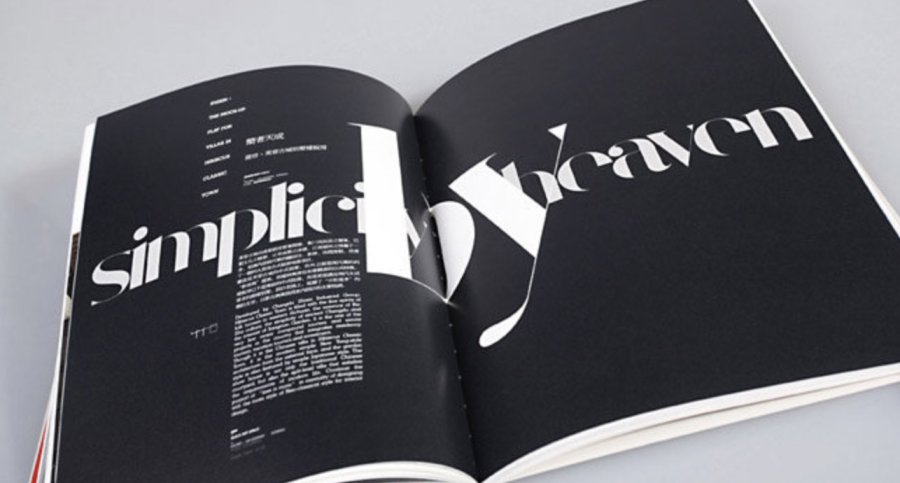
先要说一说汉字与拉丁字母的区别:字母是一种纯粹发音符号,每个字母本身并没有意义,单词的意义来自于这些字母之间的横向串式组合,而汉字的组字方式是以象形为原始基础,也就是每个字都具有特别的意义,一个简单的字可能在远古时代就代表了一个复杂的生活场景,因而它也是世界上最形象的文字。两者之间的阅读方式和解读方式都有本质的不同,因此,汉字的编排不能照搬英文的编排方式,它们两者之间在编排上有一些客观的区别。
首先,就是同样字号的实际大小不同,英文因为都是字母,字母的构成结构非常简单,一般在印刷上3号大小的英文都能清晰可辨,而汉字因为结构的复杂,在印刷上5号字已经接近辨认极限了,因而在设计时汉字因为要考虑可阅读性,在设计中就不如英文的字号大小灵活多变。还有英文字母线条比较流畅,因为弧线多,所以画面容易产生动感,这一点上比汉字生动多变。
第二,就是英文编排容易成"段",因为英文每个单词都有相当的横向长度,有时一个单词就相当于中文一句话的长度,单词之间是以空格做为区分,所以英文在排版时,哪怕是一句话,也大多做为"段"来考虑编排;而这点中文就完全不同,中文的每个字占的字符空间一样,非常规整,一句话的长度在一般情况下是不能拆成"段"来处理,所以中文在排版的自由性和灵活性上比不上英文,各种限制严格得多。虽然现代设计中有大量的对汉字进行解构的实验作品和商业作品,但总体来说,还是不能大量推广,毕竟,这种实验牺牲的就是人们习惯的汉字阅读的方便性。汉字的整体编排容易成句、成行,视觉效果更接近一个个规则的几何点和条块,而英文的整体编排容易成段、成篇,视觉效果比较自由活泼,有更强的不连续的线条感,容易产生节奏和韵律感。
第三,就是英文的篇幅普遍比相同意义的汉字的篇幅要多,在设计时,英文本身更容易成为一个设计主体,而且因为英文单词的字母数量不一样,在编排时,对齐左边那么右边都会产生自然的不规则的错落,这在汉字编排时不太可能出现的,汉字编排每个段是一个完整的"块",很难产生这种错落感。
第四,汉字的编排规则比英文严格复杂得多,比如段前空两字,标点不能落在行首、标点占用一个完整字符空间,竖排时必须从右向左,横排时从左向右等等,这些规则也给汉字编排提高了难度。而英文段落在编排时只能横排,只能从左向向,段前不需空格,符号只占半个字符空间,这给英文编排提供了更大更灵活的空间。这些区别在设计时都需要特别注意,不要照搬英文的排版模式来编排汉字,处理不好就会不伦不类!
那么对于汉字,究竟应该以一种什么样的原则和原理来进行编排才能使字、句、段、篇看起来美观清晰呢?本人在实践中,有一些经验可以拿出来与大家商讨,我在进行汉字编排时一般遵循的流程是:理解——分类——粗排——精确细排——校对。
1、理解:在进行文字的编排之前,首先要理解文字的内容。我见过很多设计师只注重版式美现而不关注文字内容,把文字一拿到手就开始编排,从不考虑文字在说什么,他们的原则是文字一定要服从于版式需要。这是不正确的设计方法,对于一篇文案稿,如果我们不去理解它的表述内容,就很容易本末倒置。
一个标题,究竟用什么字体?用多大字号?横排还是竖排?这些是由整体版面气质和文字表述的内容所共同决定的,而不是按我们的惯性思维理解,标题一定要大,要突出,要用粗壮的字体。
我们要深刻理解文字到底在说些什么,才能为我们选择字体字号提供依据,才能让文字的视觉感受与表述内容保持统一,才能为我们选择合适的插图提供指导方向。当然这种理解不是表面性的理解,还是真正吃透它所表达的意思,有时一些文字的意义是指东道西的,表面上是说这件事,其实它真正想表现是却是另一个道理,这就需要设计师有较强的理解能力。
2、分类:分类也就是把我们理解的文字段分成几个层级,并为其分配相应的占用空间和大致的视觉位置。谁是主标题,谁是广告词,谁是副标题,谁是内文,内文的组成结构是怎样的,是否需要进行视觉归纳或者是内容归纳等等,把这些问题搞清楚了,我们就可以为把这些文字分类成几个层级。
第一级是最重要和突出的,比如主标题、广告词、副标题等,第二级是对第一级的辅助说明或者是次于第一级的,比如内文和某些特别需要强调的电话号码等,第**是最次要的,比如跋、通联、页码、旁注等等,一般情况下分成三个层级就足够了,但有时会有一些很专业的技术图表和技术参数类的文本编排就另当别论了。
需要特别说明的是,这种分类并不是绝对的,只是一个模糊、大概的基本轮廓,可以让我们了解到编排对象的在版面中的功能和意义。
最后要做的就是为各个层级的文字内容分配视觉空间,如果有插图配合的话,应该同时考虑插图和文本的空间占用(在这个过程中,最容易出现的问题就是,很多设计师喜欢先把插图定位得很死,把空间都计算好了,在编排文字的时候发现文字的空间不够,这时只能到处找多余的空间把文字硬塞进去,或者牺牲文字的字号大小来妥协,最后的效果就是到处都很挤,到处都不合理,这些对于新手来说要特别注意,文本的容量和插图的容量一定要同时考虑,在有必要的时候一定要对插图的空间进行调整,不要舍不得,整体效果永远都要比局部的效果重要)。
这里的空间分配的原则就是:每个文本元素都一定要有相对独立的空间,要让它看起来本来就应该在那儿,那块空间本来就是为它而留下的,而不是让人感觉是没有地方放了硬塞在那儿的。这是一个考验设计师整体调控能力的过程,因为空间是固定不变的,而每个元素之间又是互动的,A元素的空间多一点就意味着另一个B元素的空间就会少一点,那么如何让其占用空间均衡合理,要需要从版面美感、视觉流程、表述内容、版面风格、阅读习惯等多方面去考虑,千万不要过早为它下定论,多实验几次才能找到最佳解决方案。
3、粗排:经历了前面的过程,设计师心中应该已经有了一个初步的构想,粗排的过程就是把这些构想视觉化,以形成一个基本的编排风格,这个过程仍然是一个创作的过程,是对前面提出的编排构想实践和检验的过程,主要是检验各个文本元素占用空间的情况是否合理,(这里要特别注意的一点是,现在已经是在做成品了,因此要随时把自已调整到做成品的状态上来,成品的实际有多大,有时在电脑上体现不出来的,要以实际的印刷经验来判断文本的大小是否合理,是否适合正常的阅读习惯)。
粗排主要是针对以下几个方面来进行:
A、对于内文,如果篇幅过长,应该考虑为其分栏:分栏的方式有两种:一种就是把整个篇幅平均分成几个相同容量的段块,另一种就是根据文本内容的结构,以自然段为基础进行分栏,也就是每一段分为一栏,这种分栏方式能产生比较灵活自由、错落有致的视觉风格,但不是所有的篇幅都可以这样来分,它只适合于自然段比较明显均衡,段落数量不多,各个段之间的文本容积相差不大的条件下才可以实现。
分栏的另一个要注意的地方就是栏宽的确定,一般来说,15-25个字的栏宽视觉效果比较适舒,超长或超短都会引起阅读的不方便。
B、字体的设置:字体的问题牵涉很广,由于篇幅有限,在这里我也只能简短介绍一些实践过程的经验与大家共勉。首先要明白的一点就是:不同的字体有着不同的性格和气质,也就是说字体是有生命的。许多设计师对使用字体很迷茫,不知道什么情况下该使用什么样的字体,其实这就是没有去真正关注字体性格的结果。
现在电脑上的字库五花八门,基本上我们所需要的字体在里面都能找到,但似乎选择的余地越大情况却越糟糕,各种字体出现在不应该出现的场合已是司空见惯!所以我们要学会区分各种字体的适合范围,一个基本原则就是字体的气质与版面的气质是否吻合?
比如说楷体,楷体是一种非常经典的字体,经过一千多年文明和无数书法大师的不断锤炼,已经非常成熟了,每一个字都经得起推敲,具有很强的文化气质,因此在做具有文化感和传统味的设计中可以使用。
宋体也是一种历经几个朝代的字体,被前人们修饰得无可挑剔,端庄秀丽,有贵族气质,还有仿宋体,刚柔结合,精致细腻,很唯美的字体。黑体是一种现代字体,刚挺稳重,有力量感,很醒目,但稍嫌笨重粗糙,但后来发展出来的等线体却非常精致耐看,很有现代小资的感觉,低调却不粗俗,且自成一派。
但有些字体在设计中却尽量少用或避免使用,比如文鼎的新字库里面的稀奇古怪的字体,非常粗俗,层次很低,然后就是综艺体、中行书、隶书之类的电脑字体,粗糙难看,气质很差。
真正经得起推敲的几种字体是:宋体(标宋、书宋、大宋、中宋、仿宋、细仿宋)、黑体(中黑、平黑、细黑、大黑)、楷体(中楷、大楷、特楷)、等线体(中等线、细等线)、圆黑体(中圆、细圆、特圆),这些字体是一些标准的基础字体,虽然普通却很耐看,一般内文都使用这些字体。
当然,也有一些未列入进来的好字体,比如方正繁秀丽体和汉鼎的繁黑变,我就觉得非常不错。
好的字体要用好的表现方式,对于每一种字体的挑选,一定要根据版面传达的内容和气质进行对照选择,不要带有个人喜好,许多平常不用的基础字体要尝试着去用,这样能加深对字体的理解,还有就是参考好的设计作品,看他们是如何使用文字的。总是就是不要乱用,要有切实可行道理,最关键就是一定要有视觉美感。关于字体,还要补充一点,书法字体和手写字体是对字体过于雷同的一种好的解决方法,某些特别的版面上,使用这种很自我的字体能让版面产生灵气和个性。
C、字号大小的确定:粗排过程中,每个层级的文本字号应该基本确定,这对于形象画册、书籍装帧设计来说尤为重要,因为这种多页的设计物需要在文字上有统一的视觉风格,每个层级的文本元素应该在不同的版面上保持相同或统一的视觉性格。字号的大小确定需要有三个依据:
一是各个层级元素之间的对比关系,a应该比b大多少,c应该比b小多少,应该要把各个层级之间的轻重关系体现出来。
二是版面整体比例关系,也就是让文字突出但不唐突,弱化但要可见。
三是成品的视觉效果,这是最重要的,比如一段内文,在报纸广告上可能8号至10号就足够了,但在海报招贴上,因为阅读距离的不同,可能需要24号字以上才能看清楚,而在形象画册上,6号至8号字都能看得很清楚,10号字都已经感觉偏大了一点。
所以根据不同的成品媒介考虑不同的字号大小是非常重要的,千万不能依赖电脑屏幕的显示效果做为最终依据,要经常培养对字号大小的敏感程度,在一个经验丰富的设计师眼里,8号字和9号字的区别是非常大的,它们代表着完全不同的表现力。总之一点,字号的大小是一种固定物理尺度,在设计中不能以单纯的感性观察作为确定依据,而要同时加入理性经验和成品概念来作为参考的依据。
另外要注意的一点是字体的不同也可能对字号大小的造成视觉偏差,一般来说,字符的占用比较满的字体(如黑体)在同等字号情况下看起来偏大,反之(如楷体)则偏小,这些在不同字体混排时经常出现,需要对其进行视觉修正,一般可以加入正负0.1-0.2的修正值就可以解决。
在编排时,字号的大小级数不能出现太多(除非你在刻意创造某些特殊视觉效果而需要进行混排),最好每个层级只使用一种字号大小,对于同一层级的不同隶属关系的文本,可以用字体进行区分,否则字号级数过多,将造成整个版面的杂乱无章。一般来说,第一层级的字号大小与第二层级的大小区别要比较大,而第二层级与第三层级的字号大小差距应该要小一点,这样可以清晰地体现出各个层级之间的区别。
D、字距和行距的再设计:这个问题是很多设计师都忽略的问题,所以要在这里重点说一说。为什么说"字距和行距的再设计"而不是"字距和行距的调整",因为这里面的变化如同中国古代的八卦阵,复杂多变,不同的字距和行距设定会产生完全不同的视觉风格,已经可以说成是一种"再设计"。
4、精确细排:这个阶段是非常重要而且是必须的,汉字编排是很讲究精确计算的,严谨完美的编排一定来自于精确的计算,这点在日本的设计中体现得尤为突出(日本文字的编排规则与汉字一样)。这个计算过程就是精确化、清晰化的过程。要计算什么呢?
在成品的习惯阅读距离内字的大小字号是否已经合理,各部分比例是否恰到好处,文本篇章在整个版面中是否和谐,各个层级的文字是否清晰明了,分栏的栏数和栏宽是否合理,各元素之间的距离是否安全得体,该对齐的部分是否已经分毫不差,字距行距看起来是否舒适,是否已经考虑过印刷成品裁切出血位后的距离,是否有需要进行视觉修正的部分,每个文本块的位置是否能完全确定下来等等问题。
这些问题都需要经过复杂周密的调整和计算,有些需要通过我们的眼睛进行判断,有些需要借助经验,有些需要校验数值,所以这个过程马虎不行,尤其对于文本量非常大的设计项目,一个地方出错,可能牵涉到所有的版面都需要调整。
5、校对:虽然这是一个很老土的话题,但是对于商业设计这种讲究效率的行业来说,是必须要坚持的,因为有时我们无意间漏掉的几个字、几句话都可能对你已经精确编排好的版面造成极大影响,可能会浪费你很多的宝贵时间去重新调整,因此,还是校对一下心里踏实些,免得以后重复许多无用功;